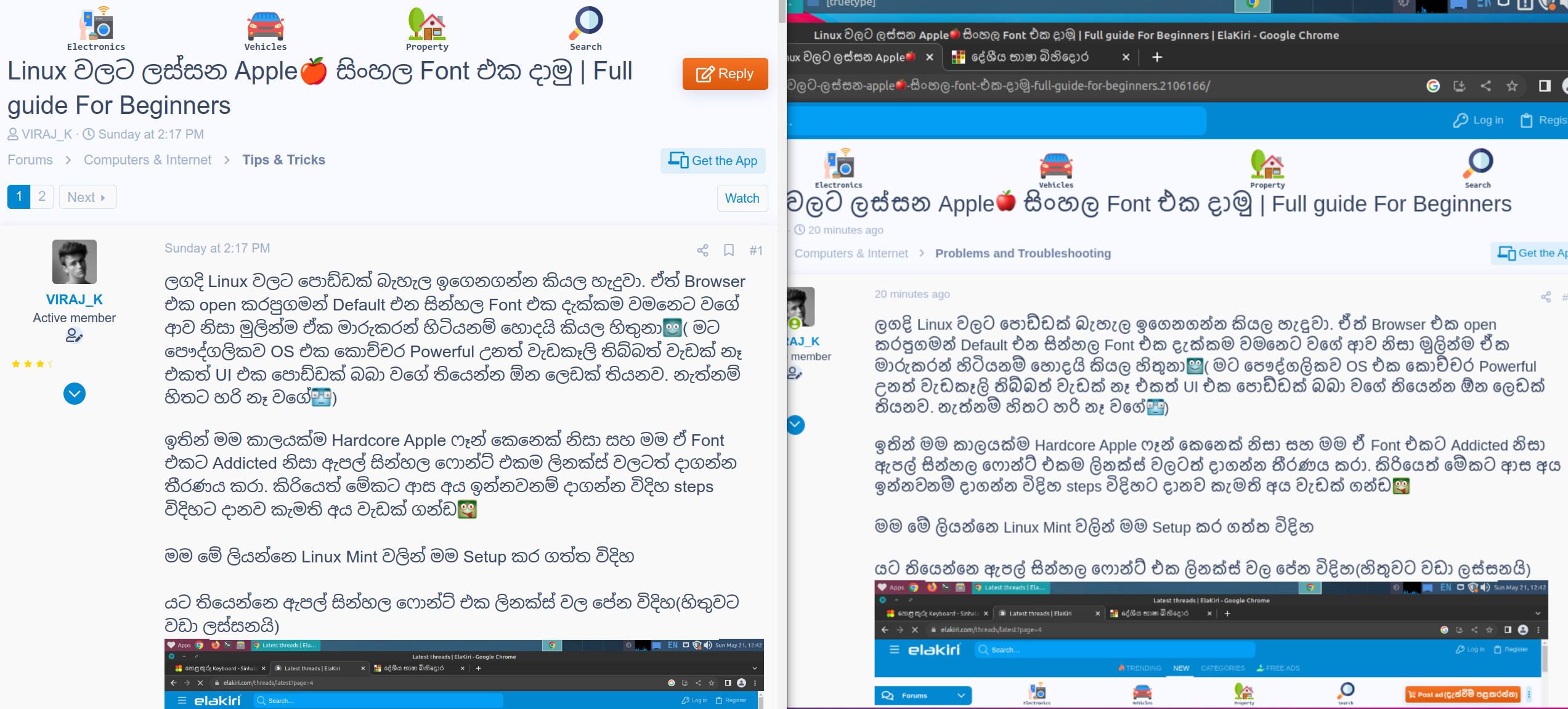
Linux වලට ලස්සන Apple🍎 සිංහල Font එක දාමු | Full guide For Beginners
Android වල එන Default සිංහල ෆොන්ට් එක වෙනස් කරන්න බැරිද. Unicode
පරන huawei android phone එකක නම් සිංහල ෆොන්ට් නැතුව install කරල තියනව අවුරුදු 7කට විතර කලින්. ඒ ක්‍රමේට නම් ඕන unicode font එකක් දාන්න පුලුවන්. දැන් නම් කරපු විදිහ මතකත් නෑ😅. අලුත් phone වල Software එහෙම ලේසියෙන් වෙනස් කරන්න බැරිද දන්නෙත් නෑ. හරිහමන් විස්තරයක් සෙට් උනොත් දාන්නම්
Me widihata Sinhala fonts okkoma remove karana eka nemei hari kramaya mekata user level font config xml file ekak hadana eka bro.
Default font එක එච්චරම අව්ල්ද?
මේ Fedora නේද? mint වලනම් Default font එක මෙහෙම පේන්නෙ. overlap වෙලා හෙනම චොර